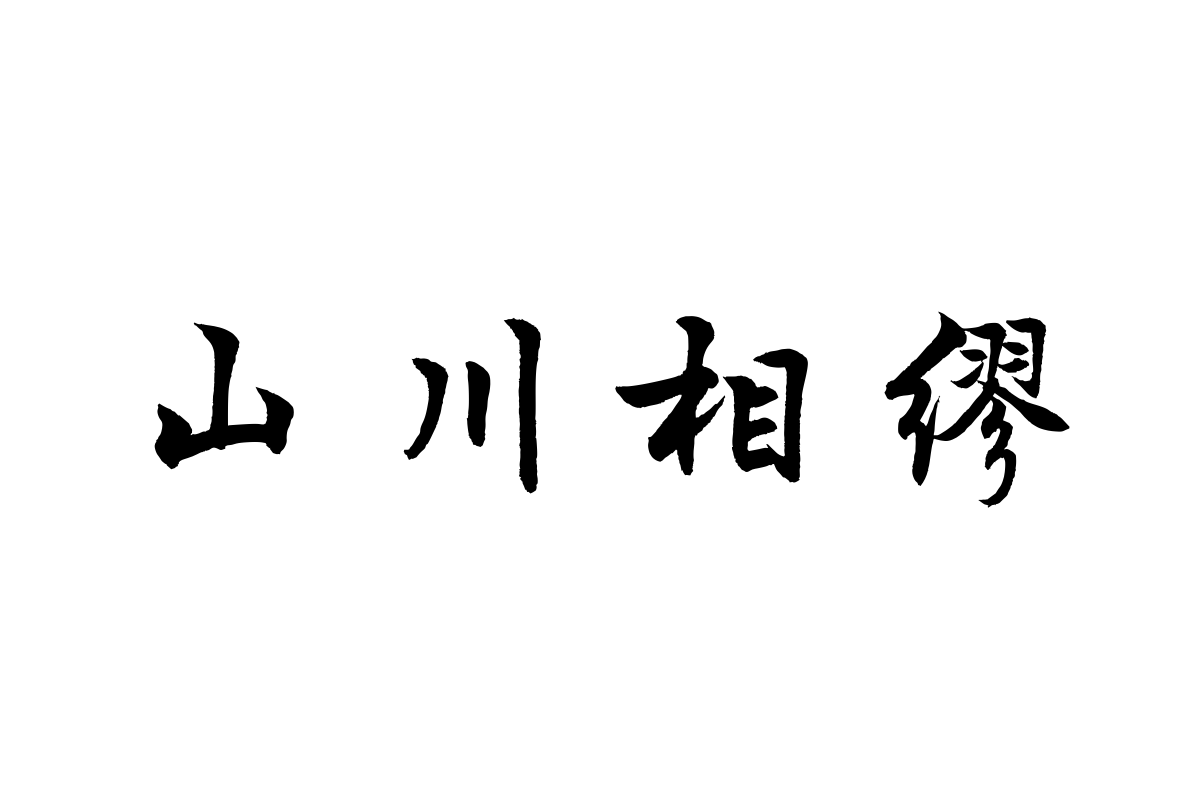
汉仪苏泽立行楷是一款具有现代感的中文字体,适用于各种商业和专业用途。这款字体的特点是笔画流畅、结构紧凑,给人一种简洁明了的感觉。它的字形规整,笔画粗细适中,既有楷书的严谨,又有行书的灵动。
这款字体的特点在于其独特的风格和适应性。无论是在广告设计、包装印刷还是网页设计中,汉仪苏泽立行楷都能展现出其独特的魅力。它不仅适合用于文字排版,也适合用于图形设计,能够为作品增添一份独特的美感。
总的来说,汉仪苏泽立行楷是一款非常适合现代设计的中文字体,无论是在商业还是艺术领域,都能够发挥出其独特的效果。